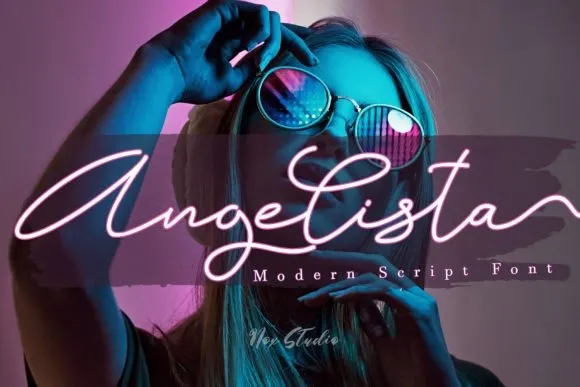
Angelista Font – Download Grátis
A Angelista Font é uma elegante fonte escrita a mão que traz uma sensação fluida e delicada. Desenvolvida pelo designer Nox Studio na plataforma de criação de conteúdo 99designs, essa fonte possui um charme casual que a torna perfeitamente adequada para trabalhos onde a leitura é essencial sem comprometer o ar despojado e acessível da mensagem. Suas características fluidas e vibrantes tornam-na uma escolha ideal para iluminar qualquer design com uma dose de frescura e vida. Além disso, a Angelista está encantadoramente codificada PUA, permitindo que você facilite o acesso aos todos os caracteres e swashes de sua letra. Perfecta para designers procurando dar um toque especial em seus projetos.